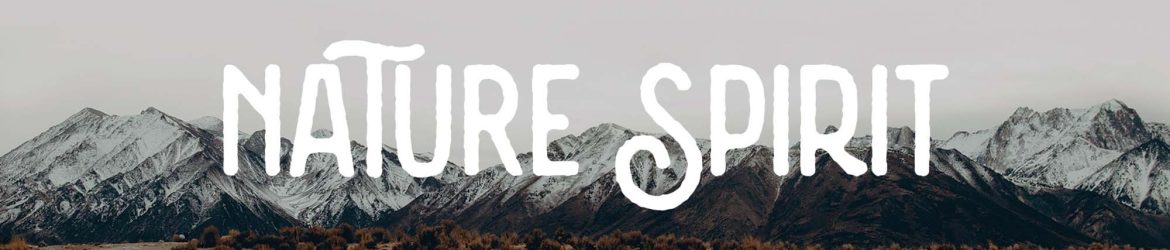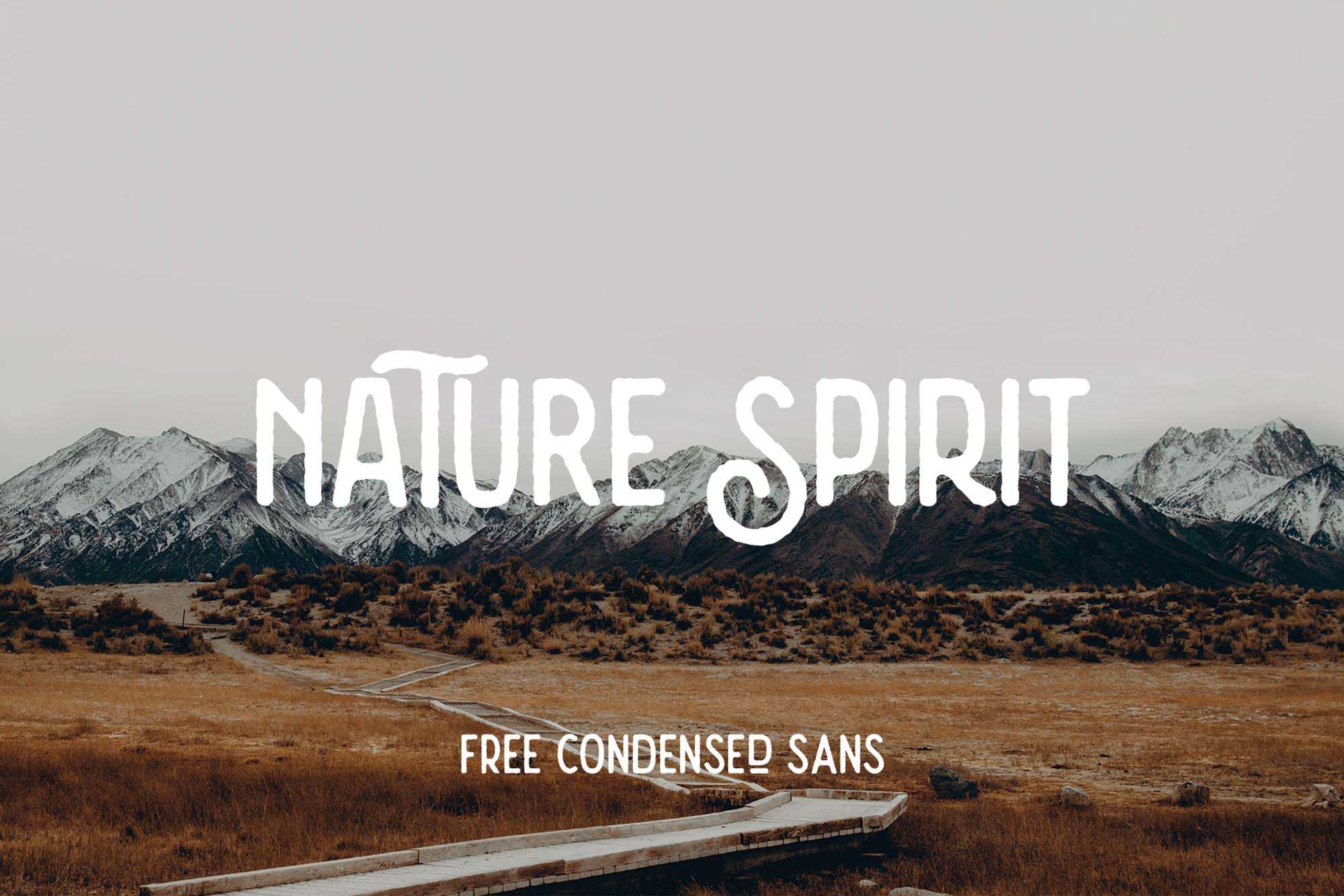
Nature Spirit Vintage Font
Nature Spirit Vintage Font é uma fonte criada por Alex Joganic que remete a uma sensação nostálgica, lembrando-nos de uma época mais calma e simples do design gráfico. Este recurso gráfico combina elementos vintage com uma elegância moderna, oferecendo um visual atraente para qualquer projeto. Como sugere seu nome, Nature Spirit tem o poder de transformar qualquer arte digital em algo vintage e autêntico, fazendo-o parecer como se ele saísse de um passado nostálgico. Este mockup pode ser usado para criar uma sensação de sofisticação vintage em aplicações digitais, sendo útil para criar materiais de marketing, logos ou qualquer outro conteúdo visual que possa ganhar um toque vintage. O design simples e moderno da Nature Spirit Vintage Font ainda consegue capturar o espírito nostálgico de uma época passada, fazendo com que ela se destaque em qualquer projeto.